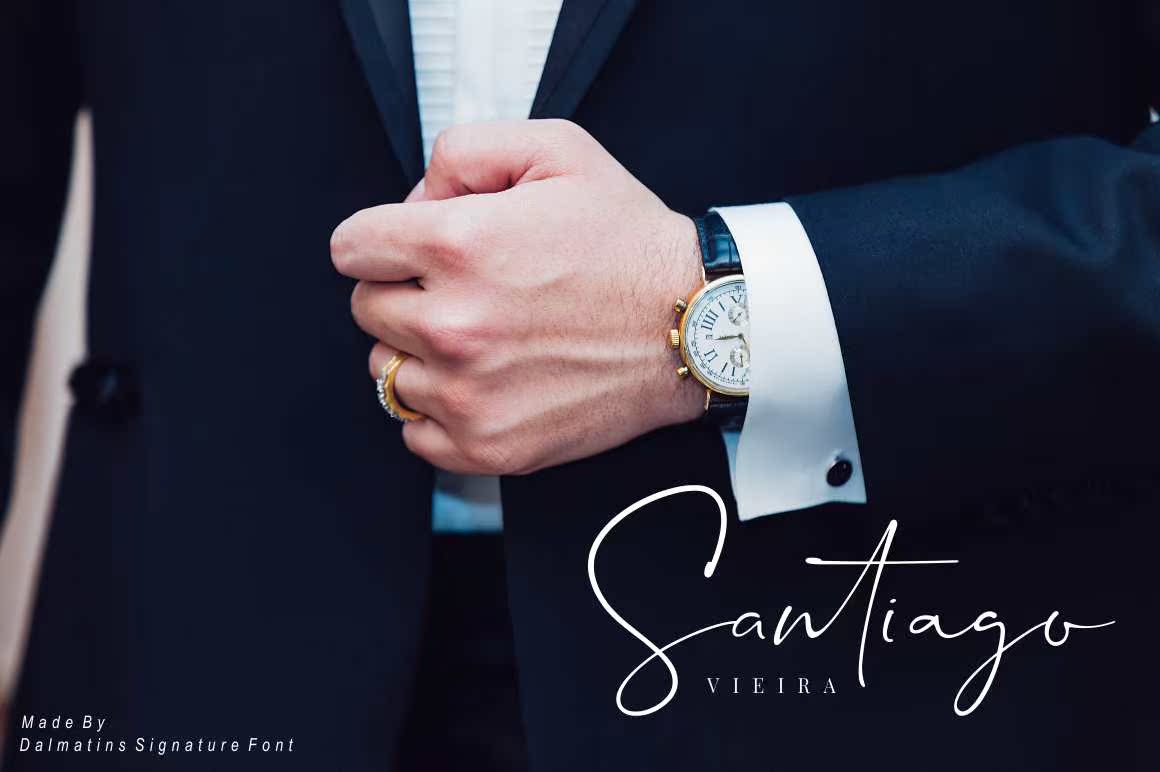
介绍达尔马汀——一种现代标志,它的优雅线条使其成为您个人品牌和众多项目的完美之选,例如:徽标、邀请函、文具、婚礼设计、社交媒体、广告、产品包装、产品设计、标签、摄影、水印、,特色和更多介绍达尔马汀——一种现代标志,它的线条非常适合您的个人品牌和其他项目,例如:徽标、邀请函、文具、婚礼设计、社交媒体、广告、产品包装、产品设计、标签、摄影、水印、特色和更多